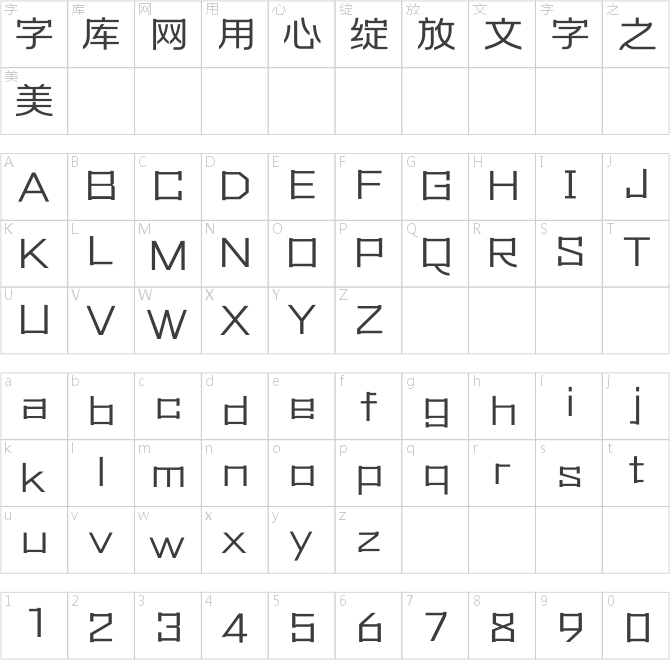
字體名稱: 方正創黑
方正創黑
方正創黑字體下載FZChuangHJW
這款字的創意風格來源于我們最常用的黑體字,在黑體的基礎上增強了字體結構的飽滿度,加強了筆畫的韻律和節奏感,以及規范度讓整體字形更加簡潔易記同時兼備藝術感。在橫豎筆畫轉角的處理上,加以傳統書法的提筆落筆,讓整體字形彰顯力量感頓挫感,在撇捺筆畫的走勢上,借鑒了宋體字筆畫的柔和度,讓整體字形摒棄黑體字的生硬,讓它更具優雅性, 在創作過程中,我們始終讓字形兼具力量與優雅并存,從而在簡潔的字形中,形成自身最大的特征。適用于產品包裝、海報視頻、大標題及周邊等領域。